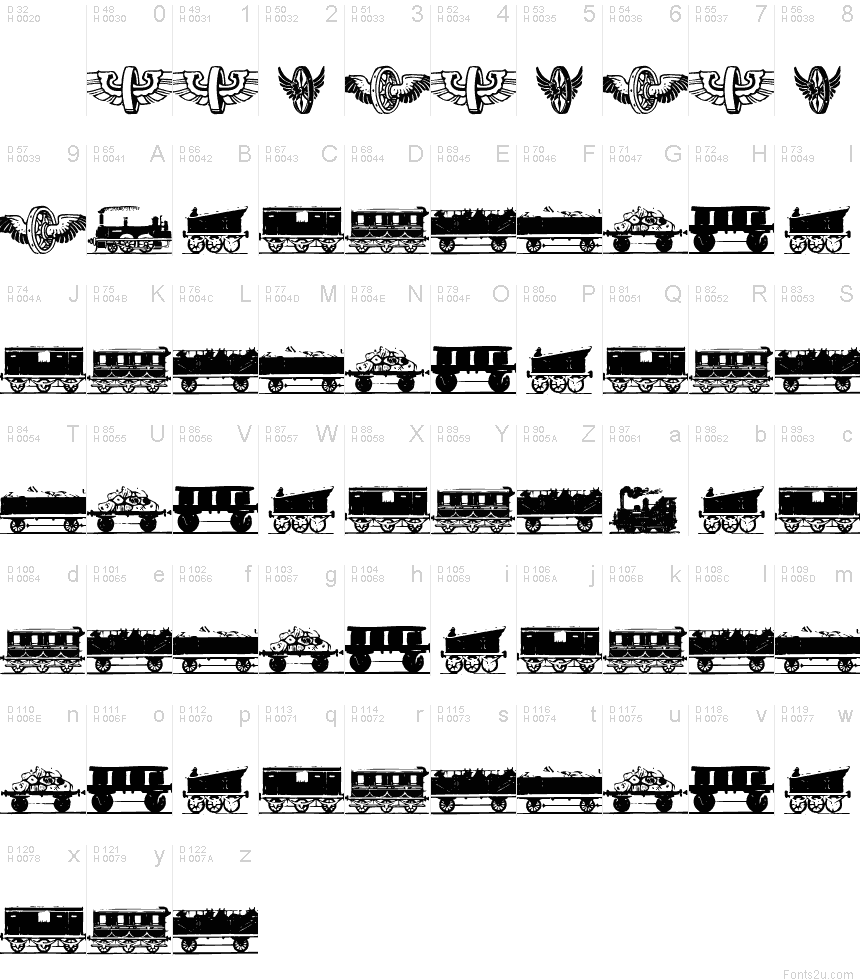
يُعد Eisenbahn، الذي صممه Dieter Steffmann من Typographer Mediengestaltung، خطاً مجانياً من نوع الرموز (dingbat) يحول كل ضغطة مفتاح إلى صورة ظلية صغيرة لقطارات عتيقة. تصطف قاطرات البخار وعربات الشحن ومقطورات الوقود وعربات الركاب مثل قطار مصغر، مع خطوط خارجية واضحة وأشكال جذابة وممتلئة قليلاً، مما يجعلها سهلة القراءة حتى بأحجام صغيرة. يتمتع الخط بطابع ميكانيكي وحنين إلى الماضي، وكأنه مقصوص من لافتات السكك الحديدية القديمة أو رسومات التذاكر.
يمكنك استخدام Eisenbahn لإنشاء إطارات قطارات مرحة وفواصل ورموز تعبيرية (pictograms) لكتب الأطفال، والمواد التعليمية، ومنشورات هواة السكك الحديدية، ودعوات أعياد الميلاد، والملصقات ذات الطابع الخاص، وتغليف الألعاب أو الحلويات. يعمل هذا الخط المجاني أيضاً بشكل رائع في لافتات الفعاليات أو معارض المتاحف عند استخدامه بحجم كبير، حيث تبرز كل عربة كأيقونة مستقلة. للحصول على مظهر متوازن، ادمج Eisenbahn مع خط sans serif هندسي بسيط واترك رموز القطارات تتولى مهمة السرد البصري.